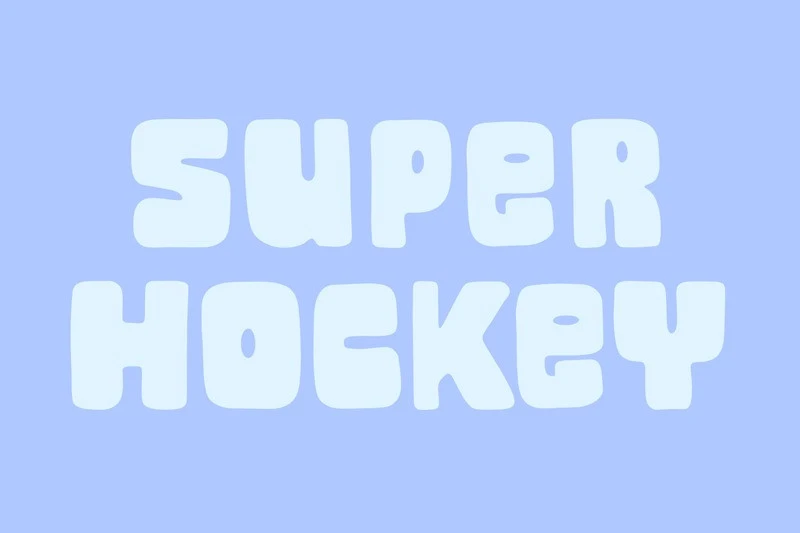
Super Hockey Font
Super Hockey Font, fsuarez913 tarafından tasarlanmış eğlenceli bir gösterişli yazı tipidir ve Fancy > Cartoon stiline aittir. Cesur, dinamik harf formlarına sahip olan bu font, sportif ve enerjik bir görünüm sunar; hokey'in hızlı tempolu ruhundan ve atletik markalaşmadan ilham alınmıştır.
Super Hockey Font, fsuarez913 tarafından tasarlanmış eğlenceli bir gösteri tipografisidir ve Fancy > Cartoon stiline aittir. Kalın, dinamik harf biçimlerine sahip olup sporcu ve enerjik bir görünüme sahiptir; hokey'in hızlı tempolu ruhundan ve atletik markalaşmadan ilham alınmıştır.